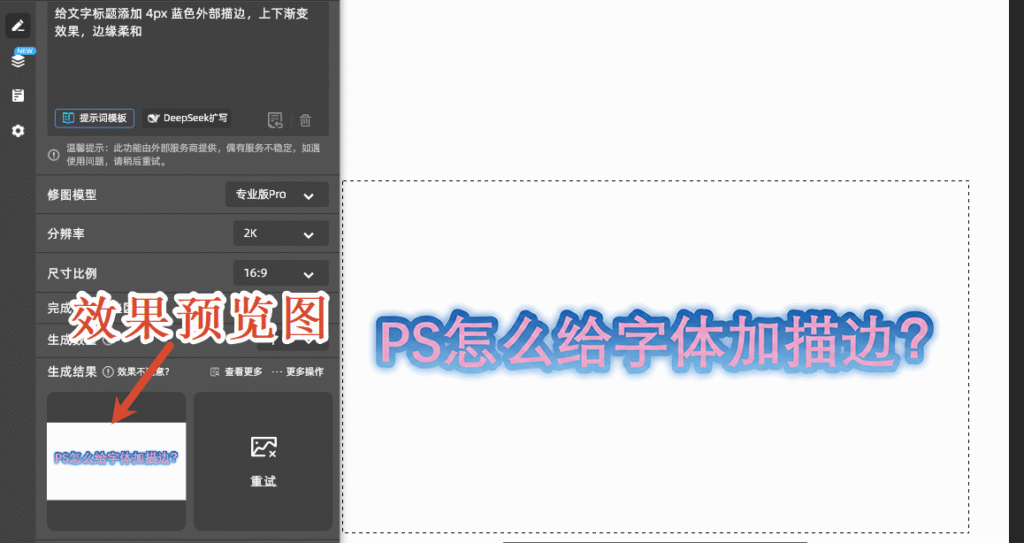
PS 字体描边怎么做?新手一看就会的2种描边方法教程
在 Photoshop 中给字体描边,是设计里突出文字、增强视觉层次感的常用操作,不管是做海报标题、电商主图文字还是自媒体配图,掌握字体描边技巧都很实用。本文详细分享 PS 字体描边的多种常用方法,还会介绍 AI 插件快速实现高级描边效果的技巧,新手也能轻松上手。
一、PS 基础方法:图层样式描边(最常用)
图层样式描边是 PS 自带的非破坏性编辑功能,操作简单,参数可随时修改,适配大部分常规描边需求,也是新手入门首选方法。
输入文字:打开 PS,用横排文字工具(快捷键 T) 在画布输入文字,设置好字体、字号和颜色,生成文字图层。
打开图层样式:双击文字图层缩略图,或点击图层面板底部fx 图标,选择 “描边” 选项。
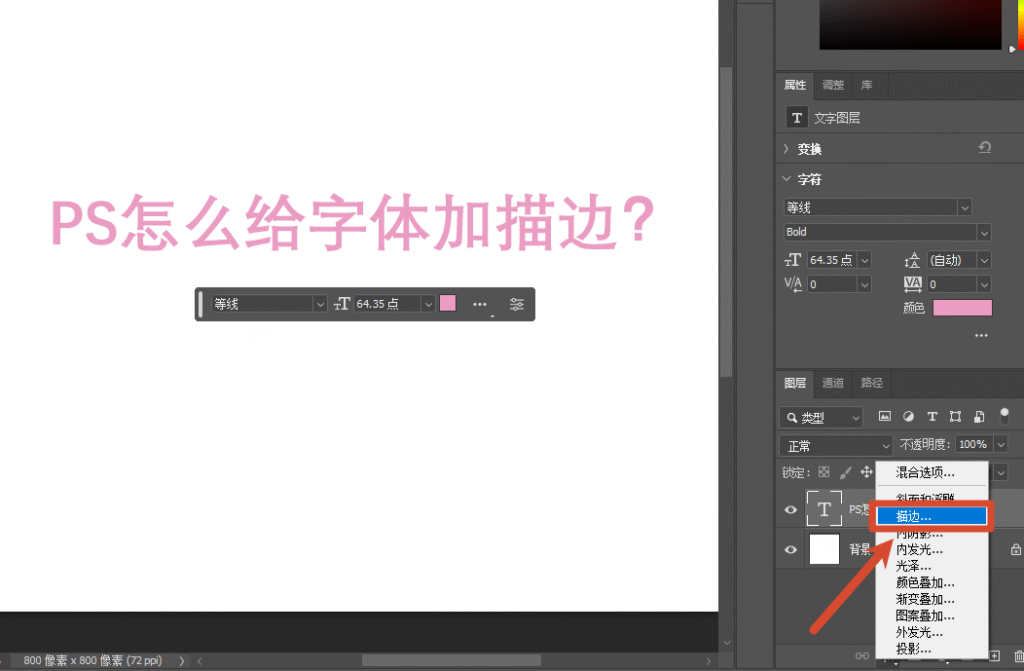
点击“fx” 图标选择 “描边” 选项
调整描边参数:
大小:控制描边粗细,小字(20px 以下)建议 0.5-1px,标题文字 2-5px;
位置:可选外部、内部、居中,外部突出文字轮廓,内部适合复古风格;
颜色:点击拾色器,选与背景对比度高的颜色,也可设置渐变、图案描边;
混合模式:按需选择叠加、正片叠底等,让描边与背景自然融合。
确认效果:勾选 “预览” 实时查看调整效果,满意后点击 “确定”,完成基础字体描边。
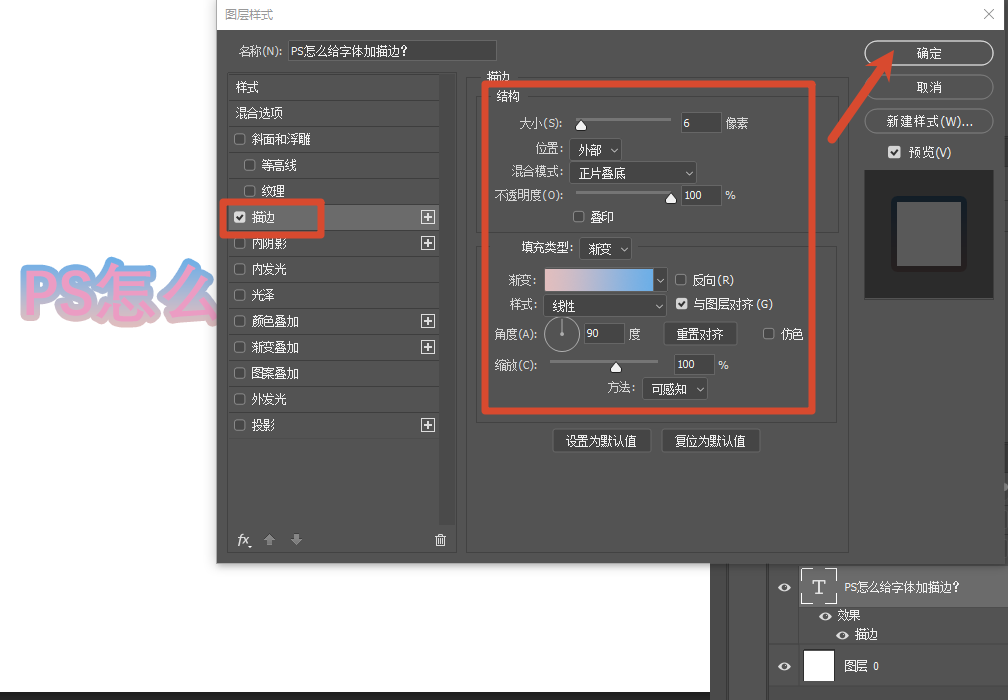
调整描边参数
二、AI 高效方法:StartAI 插件一键高级描边
传统描边做渐变、虚线、质感描边等复杂效果时,步骤繁琐且效果受限。StartAI 作为深度适配 PS 的 AI 插件,无缝融入 PS 工作流,无需复杂参数调整,一键就能生成高级字体描边效果,兼顾新手易用性与专业级质感。
StartAI插件界面
(一)StartAI 插件字体描边操作步骤
输入需求:在修图需求指令框输入描边需求,如 “给文字标题添加 3px 蓝色外部描边,渐变效果,边缘柔和”。
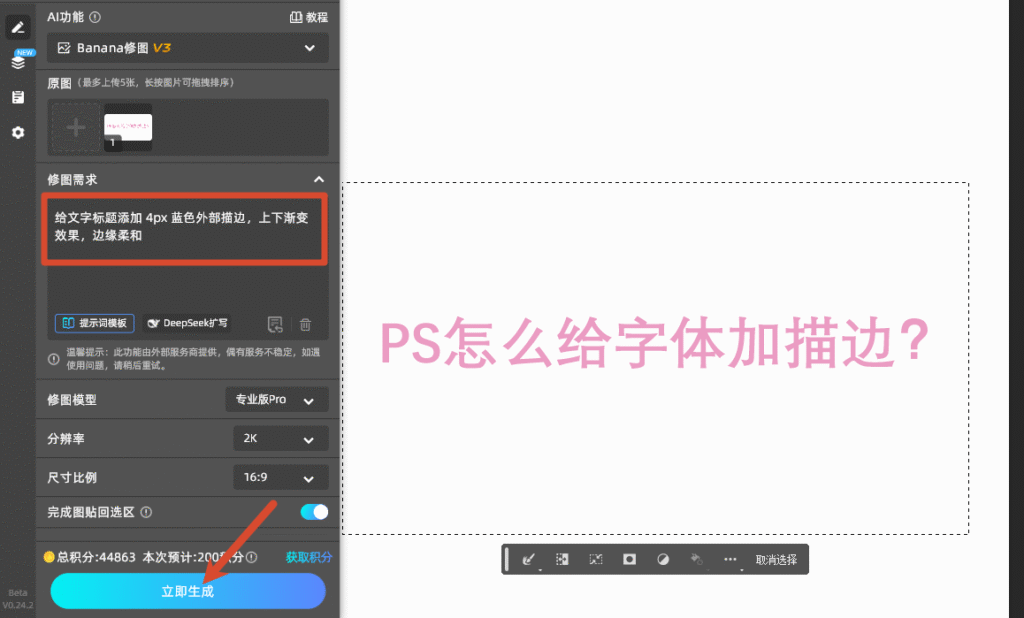
Banana修图
生成效果:点击 “生成” 按钮,AI 自动处理,几秒内生成预览效果。
Banana修图效果图
微调确认:对比预览效果,按需调整关键词(如修改颜色、粗细),生成的效果图直接同步到 PS 画布。
(二)StartAI 插件字体描边优势
操作极简,零基础上手:无需记忆复杂菜单和参数,输入简单关键词(如 “蓝色渐变粗描边”“霓虹发光描边”),AI 自动生成精准描边效果,新手 1 分钟就能完成。
非破坏性编辑,灵活调整:描边效果生成独立图层,支持二次修改颜色、粗细、透明度,不破坏原始文字图层,方便反复优化StartAI。
三、PS 字体描边实用小技巧
1. 多层描边叠加:用图层样式添加多层描边,内层细描边 + 外层粗描边,打造立体层次感,适合海报主标题。
2. 渐变描边搭配:用图层样式的 “渐变” 填充类型,设置双色或多色渐变描边,让文字更具时尚感。
3. 描边与投影结合:添加描边后,搭配 “投影” 图层样式,增强文字立体感,避免文字与背景融合。
四、总结
综上,PS 字体描边从简单到复杂,可灵活选择方法:基础需求用图层样式描边,精准需求用选区描边,追求高效和高级质感,优先选择 StartAI 插件,一键解锁多种高级描边效果,大幅提升设计效率和作品质感。